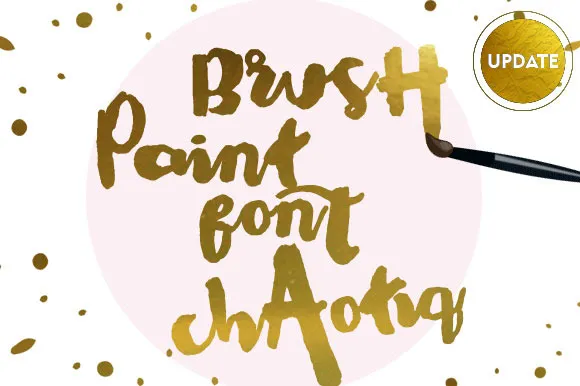
Chaotiq Modern Paint Brush Font – Download Grátis
A Chaotiq é uma fonte moderna com estilo de pintura a caneca que traz beleza natural à sua produção visual. Criada pelo designer Hamilton, esta fonte é perfeita para quem busca um ar descontraído e versátil no seu design, combinando elegância contemporânea com um toque autêntico da arte tradicional da pintura a caneca. Com o Chaotiq Modern Paint Brush Font, você pode explorar diferentes estilos de escrita e adicionar uma personalidade única à sua tipografia. Esta fonte traz um equilíbrio entre modernidade e natureza, tornando-a perfeita para uso em design gráfico, editorial, e até mesmo como base para criações digitais de arte digital. Com a Chaotiq Modern Paint Brush Font, você pode experimentar uma nova maneira de expressar sua visão visual, unindo a força da caneca ao espírito moderno. Seja para criar materiais impressos ou desenvolver designs digitais inovadores, essa fonte traz um toque autêntico e único à sua criação, proporcionando diversidade e charme em qualquer aplicação que você decida usar.